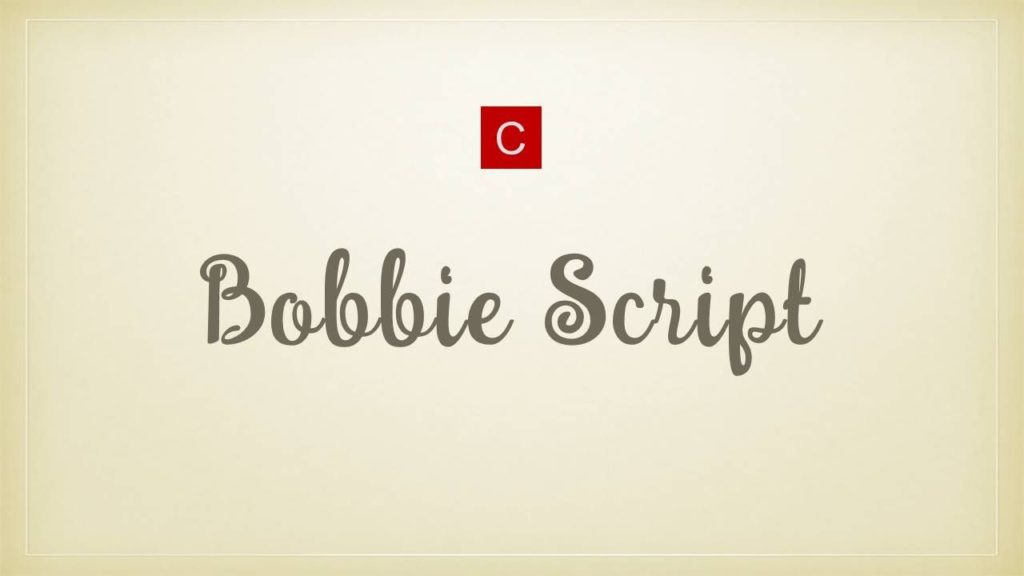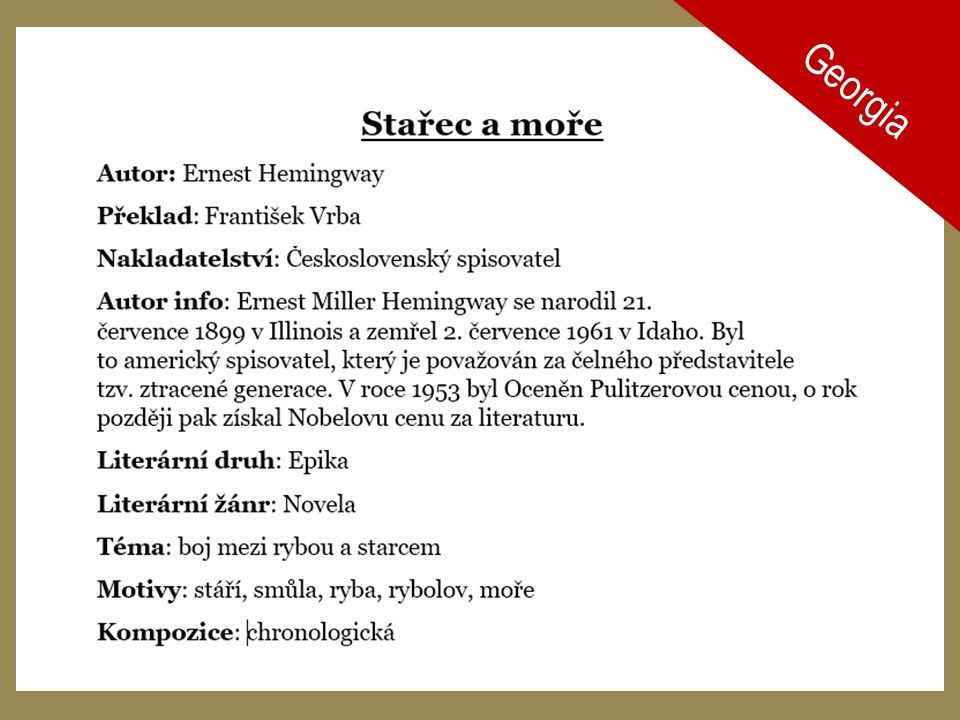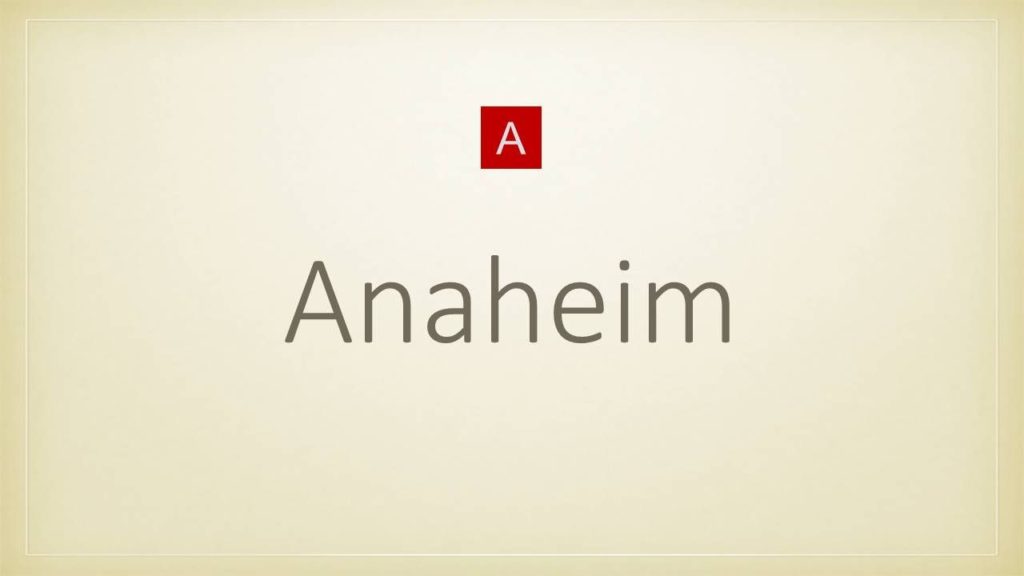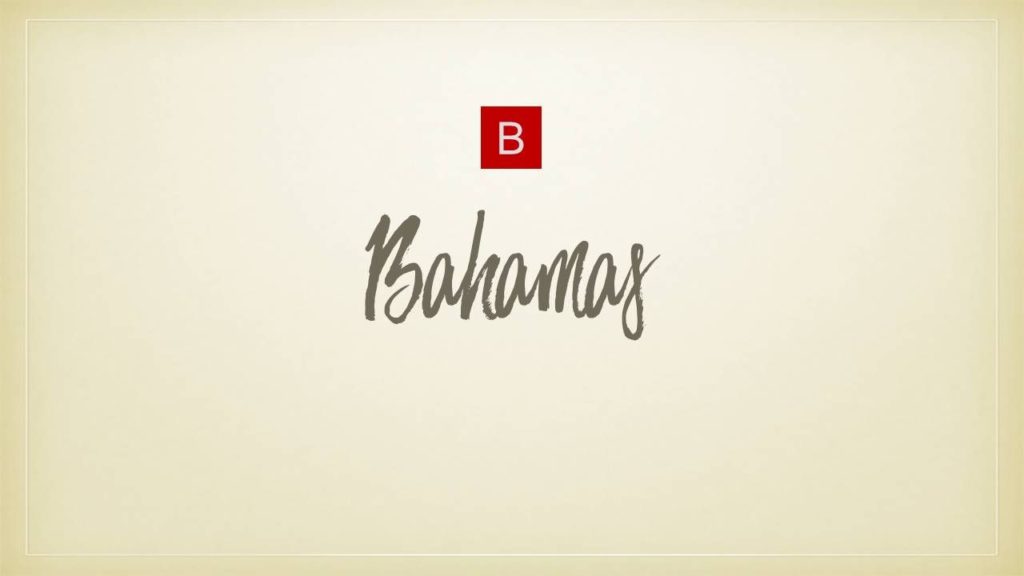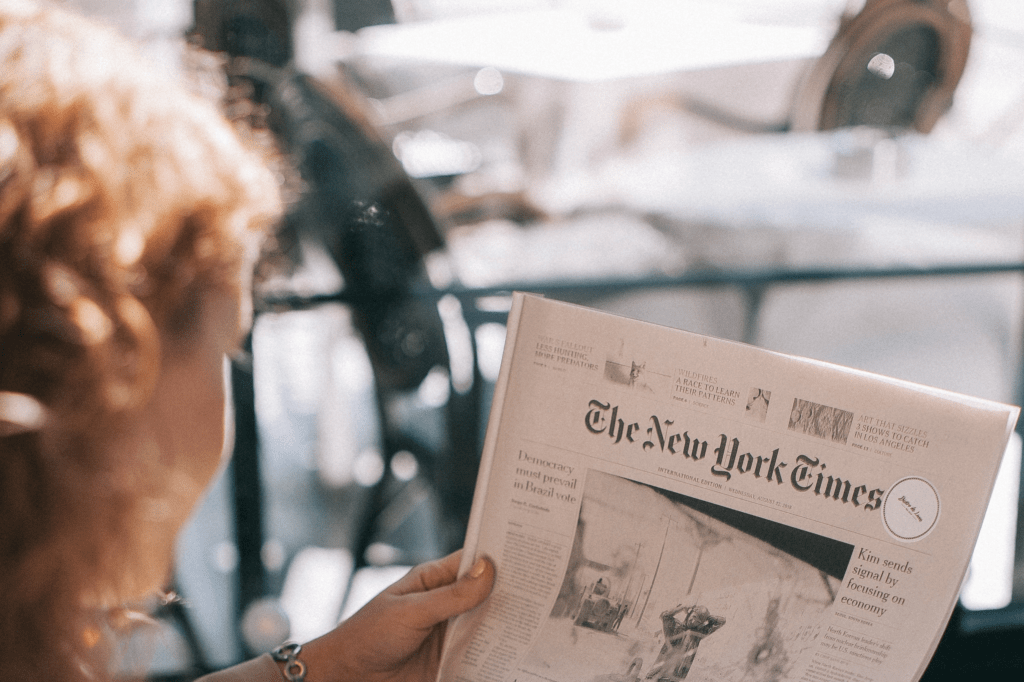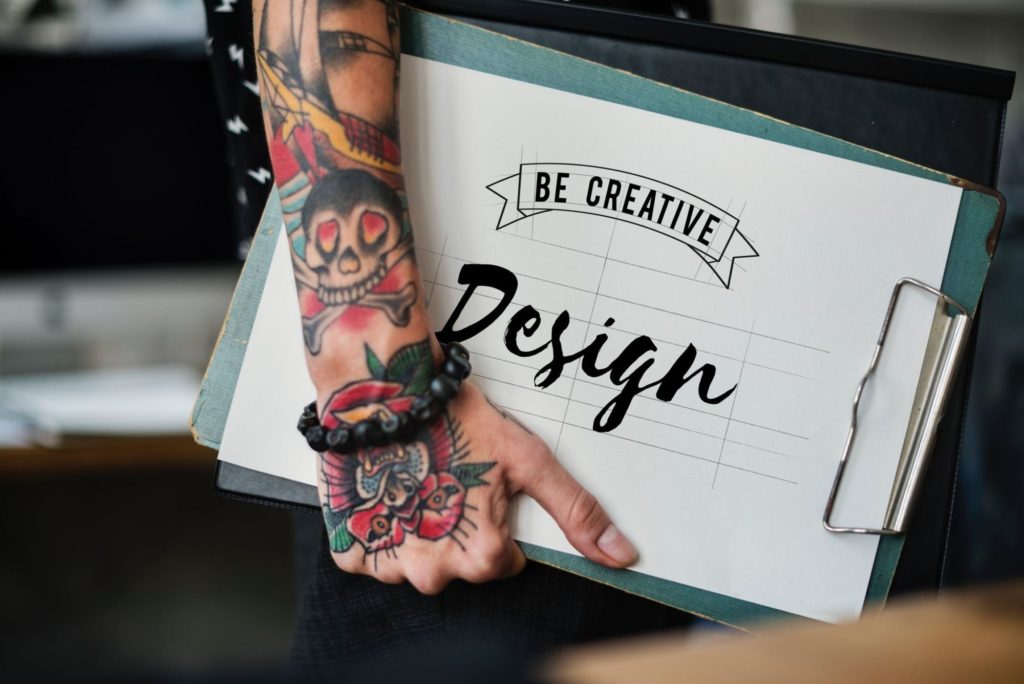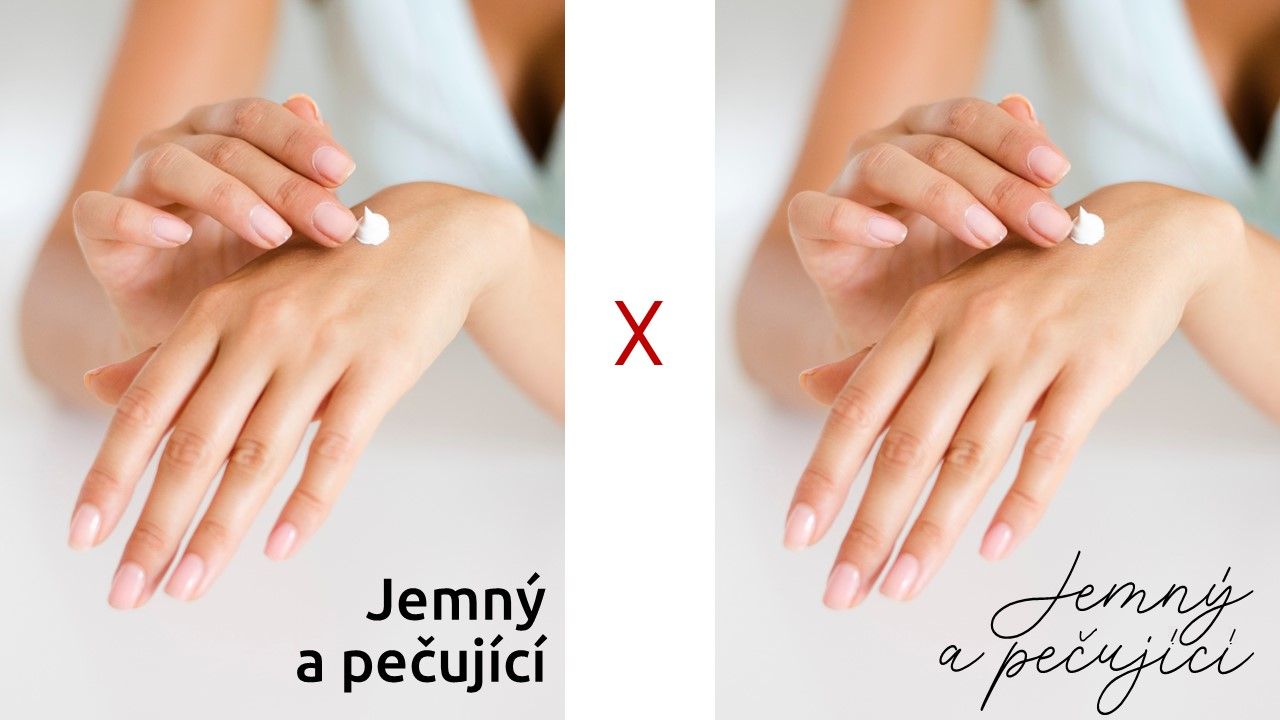
Kdyby byla anketa pro grafiky a webdesignery o nejčastější dilema, které při práci (a se zákazníky) řeší, věřím, že by v nejužším finále skončily tyto dvě otázky:
„Jakou barvu?“
a
„Jaký font?“
Barvy a fonty jsou prostě všude. Ať upravujete texty v brožurce, vytváříte grafické prospekty, webové stránky. A přestože existují tisíce stránek o psychologii barev, stačí trošku googlit, o psychologii fontů nenajdete téměř nic. Pojďme to napravit.
Ale nepovídejte. Možná neslyšel, ale určitě se s ní denně potkáváte. Jenom jí nevěnujete pozornost. Psychologie fontů není jen pro vyvolené, setkávají se s ní i obyčejní smrtelníci.
„Neváhám říct, že font v eseji zcela jistě ovlivňuje její (= eseje) ohodnocení, i když na nevědomé úrovni.“
Phil Renaud
„Může font sám o sobě zásadně ovlivnit to, jak vnímáme obsah sdělení? Můžeme oddělit formu a obsah textu?“
Zjistil, že vybraný font má obrovskou moc ovlivnit vnímání čtenářů. Vyberete seriózní font, věří vám. Vyberete neformální font a důvěra v pravdivost informací v textu klesne o polovinu.
Z hlediska designu je zásadní využít potenciál, který fonty nabízí – pokud vystihneme osobnost fontu tak, aby korespondovala s nábojem textu, stává se mnohem působivějším a má daleko větší dopad.
(Eric Jaffe, The Science Of Comic Sans)
*****
Možná jste skvělí grafici, máte estetické vnímání, vzdělání a praxi. Anebo máte intuici, která vám ukazuje ideální kombinace barev i fontů. Tak proč byste se měli zabývat psychologií fontů?
Můžeme sepsat černé na bílem 3 fakta.
Ne domněnky, ne předpoklady, ale fakta.
Podívejte se na následující tři fonty:
Jasně, že vám hned naskočí, jestli se vám líbí nebo ne a jestli by se daly někde použít. Ale dokázali byste jasně definovat:
Psychologie fontů není o hledání „nejhezčího, nezvyklého, atraktivního, zajímavého…“ fontu. Takového, který se vám bude líbit. Nehledáme font, ze kterého si všichni sednou na zadek.
Hledáme font, který tvoří identitu značky.
Intuice i estetické cítění jsou velmi subjektivní. A pokud pracujete pro klienta, není důležité, jestli se VÁM font líbí anebo ne.
Protože klient může mít úplně jiný vkus, než vy. A jeho klienti, pro které je výrobek, plakát, web určený, mají možná ještě úplně jiný vkus a očekávání. Krásně to popsal Ondřej Ilinčev:
Klient: „Proč jste vybral zrovna tohle písmo?“
Designér: „Prostě se mi to líbilo.“
Klient: „Mně se nelíbí.“
Designér: „Mně jo.“
Klient: „Ale já vás platím.“
Tahle bitva nejde vyhrát.
Jakmile nevíte, proč jste vybrali právě ten jeden jediný font, něco je špatně.
Klient potřebuje vědět, že jste font nevytáhli z klobouku jako králíka. Že víte přesně, proč právě tento je pro něj ten pravý a proč by ho měl použít. Potřebuje slyšet, jaké hodnoty představuje, a jak zapadá do celého vizuálního stylu. A abyste toto mohli klientovi vysvětlit, potřebujete to vědět vy sami.